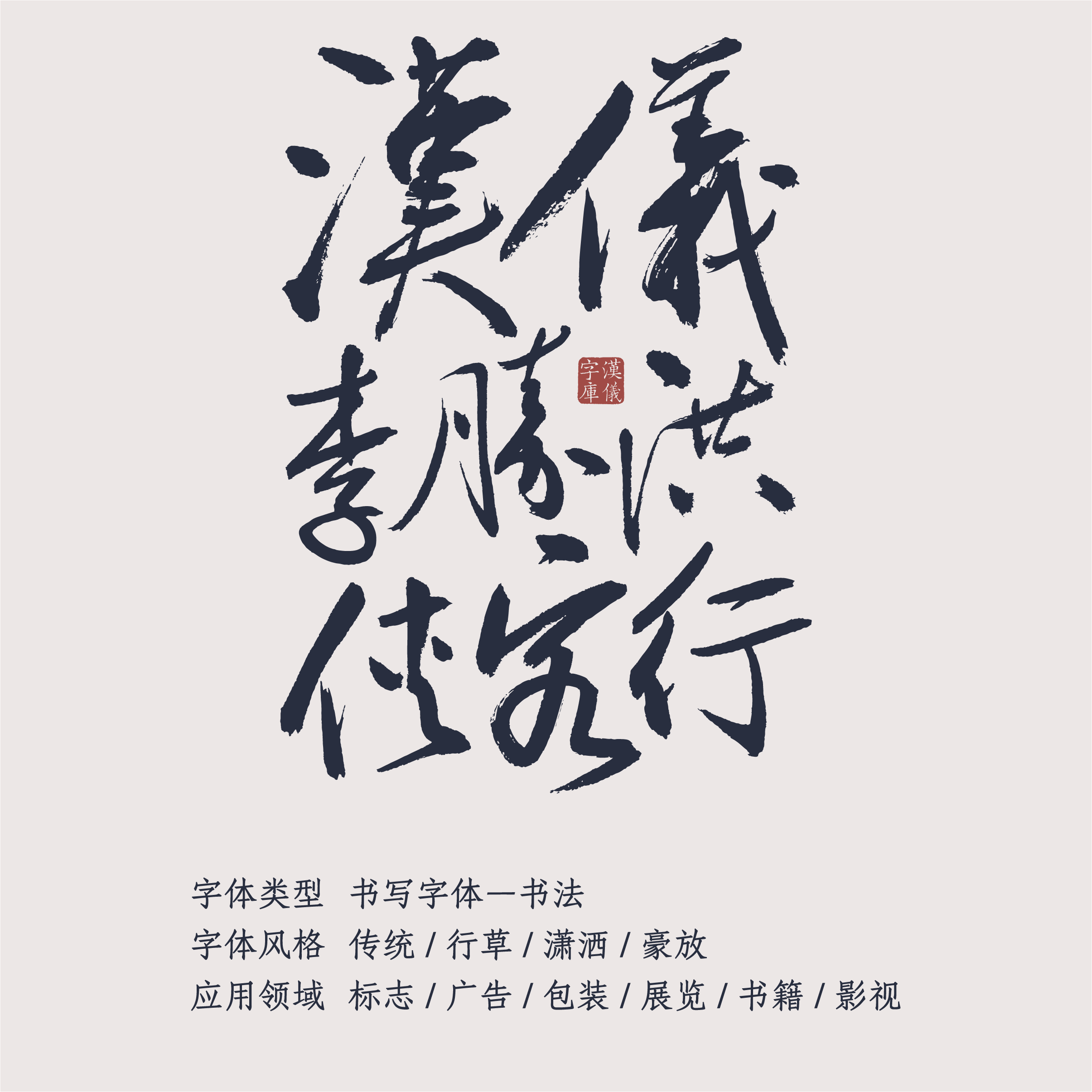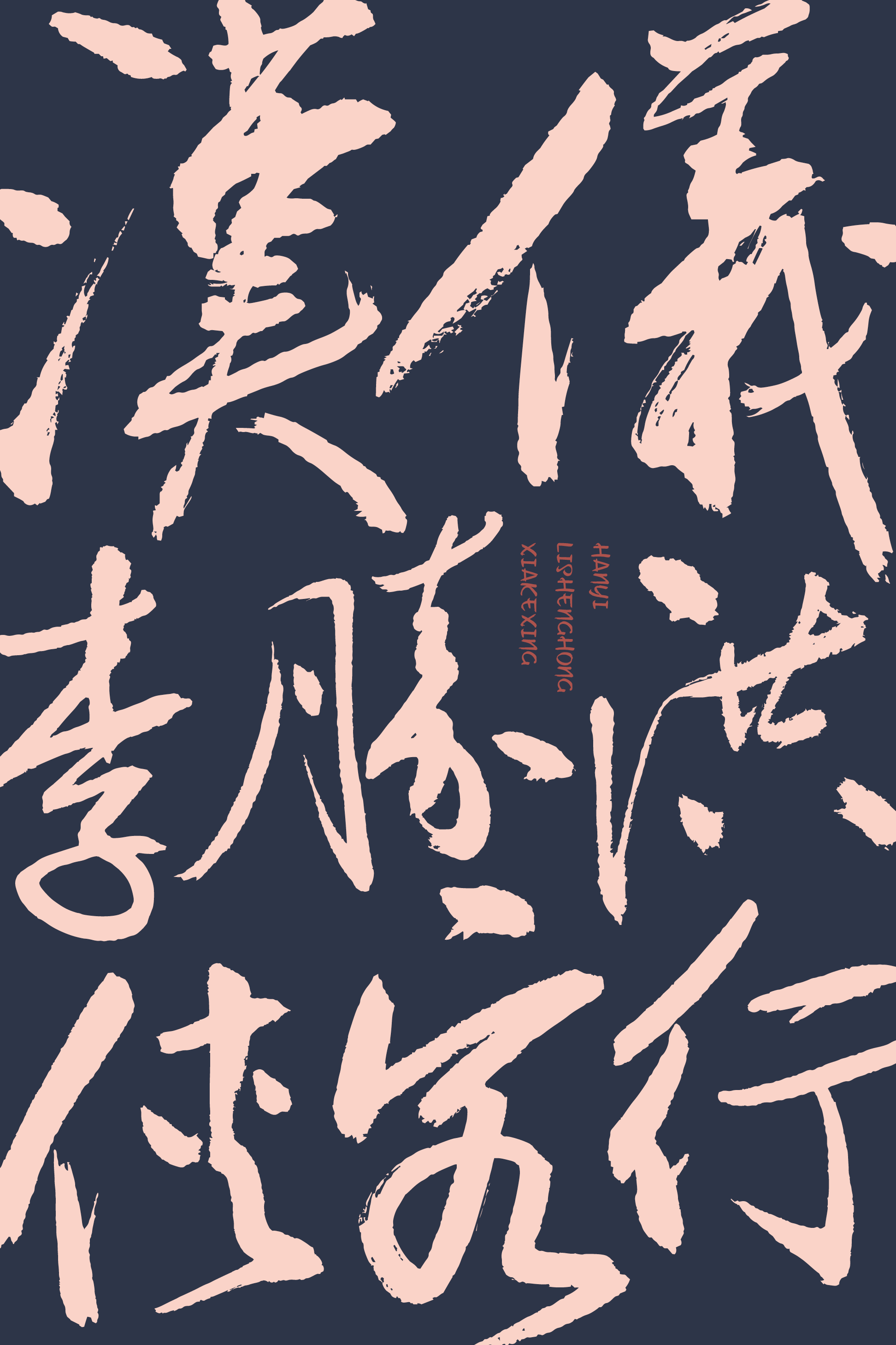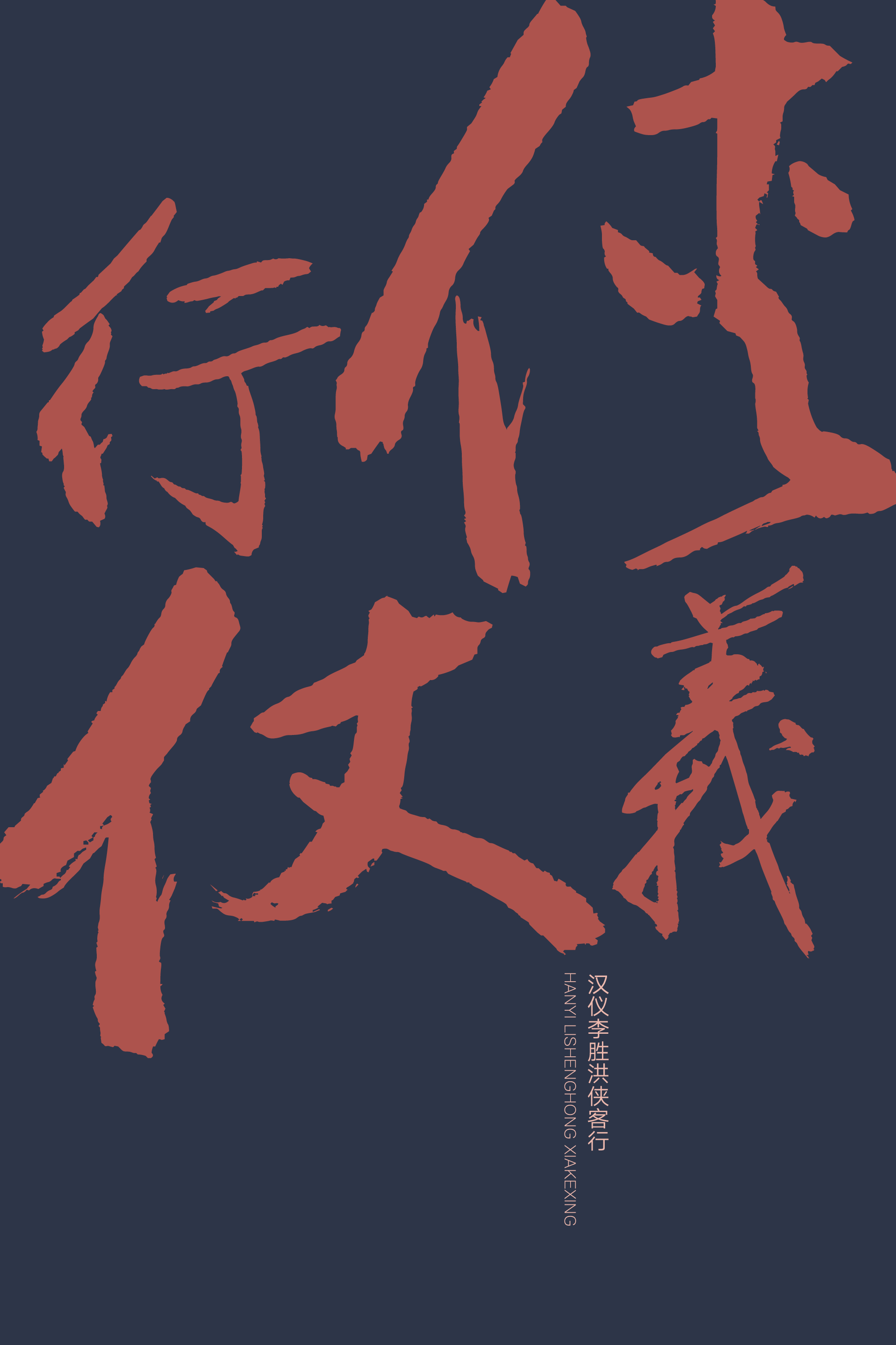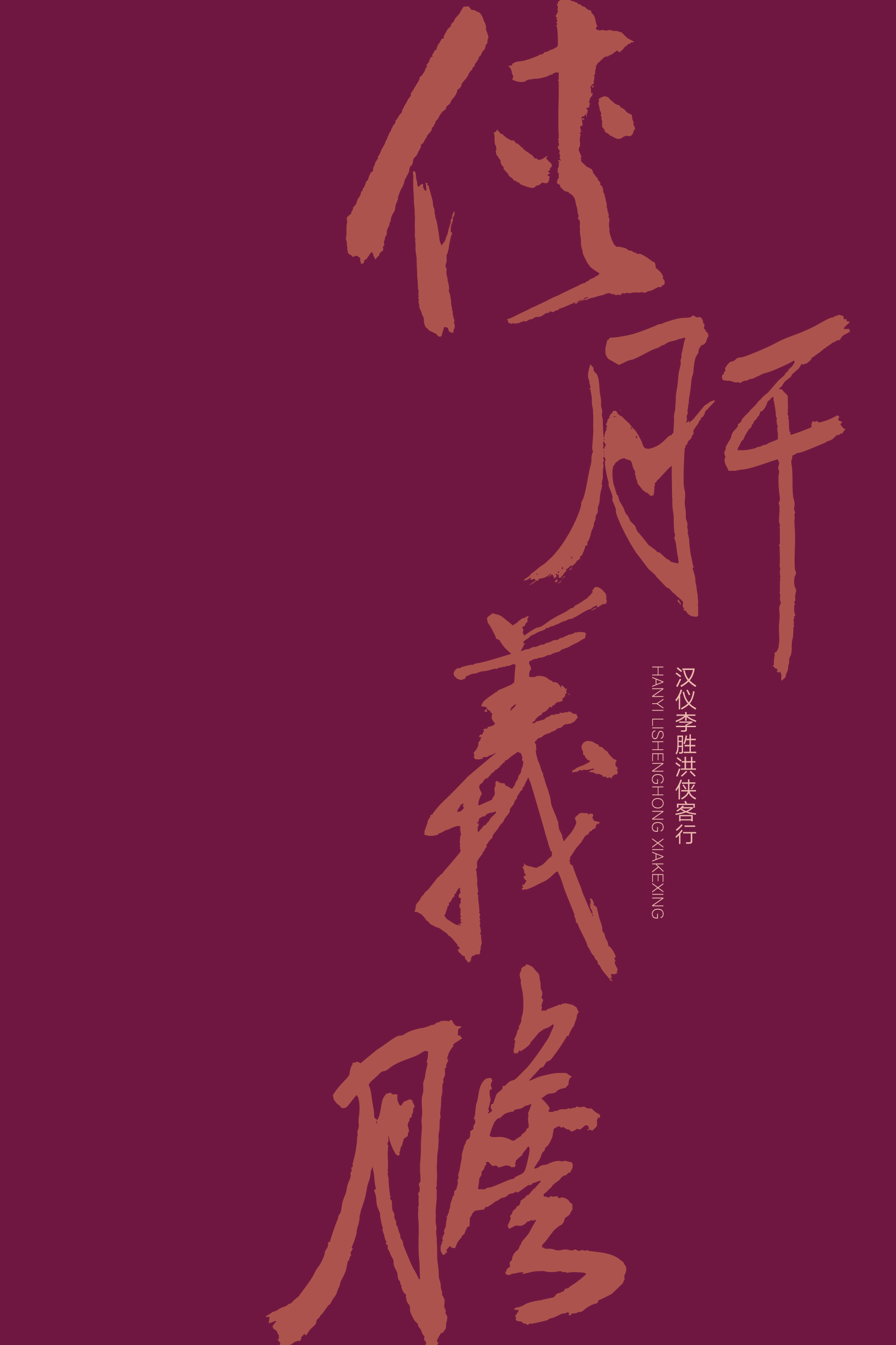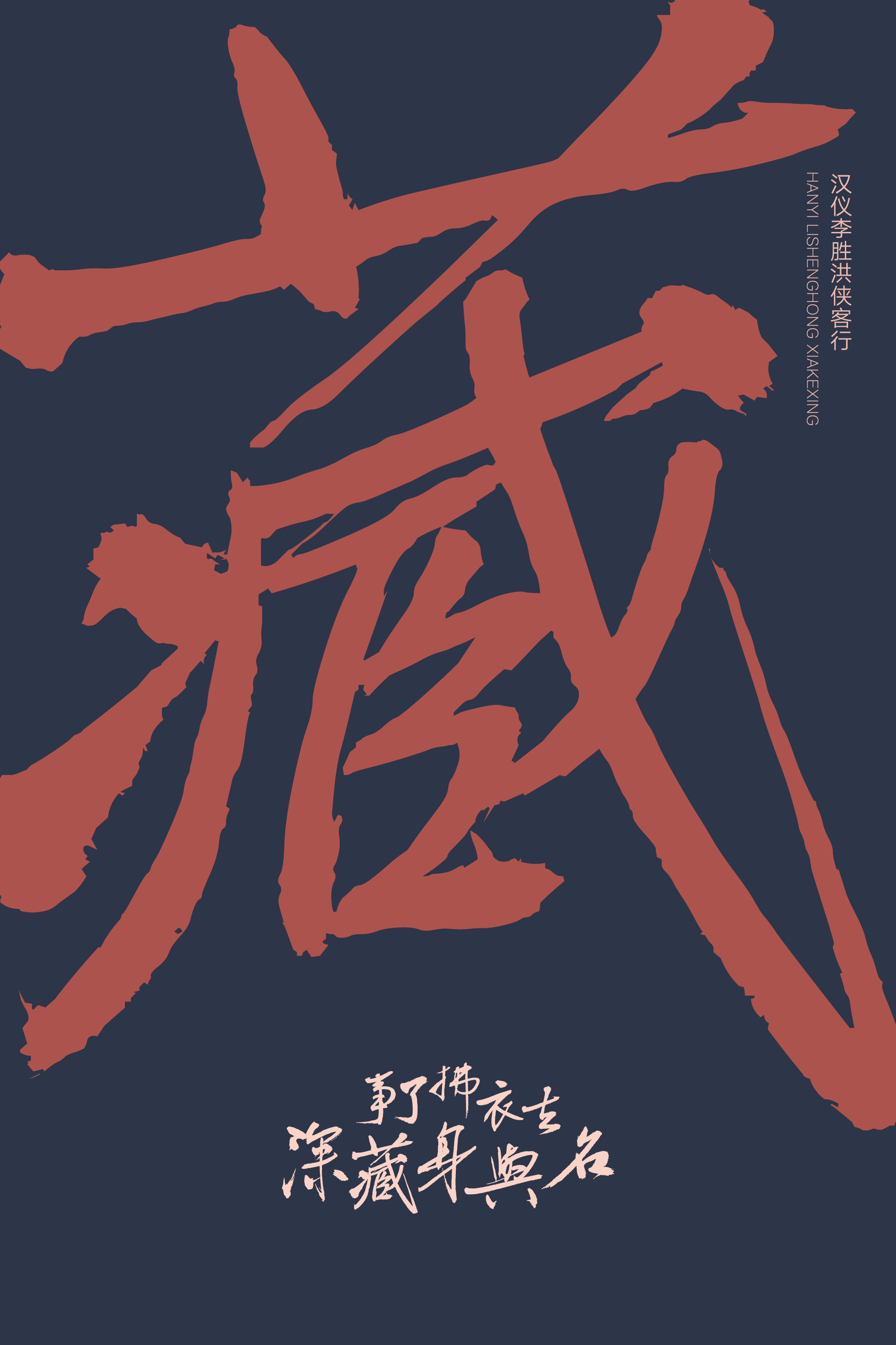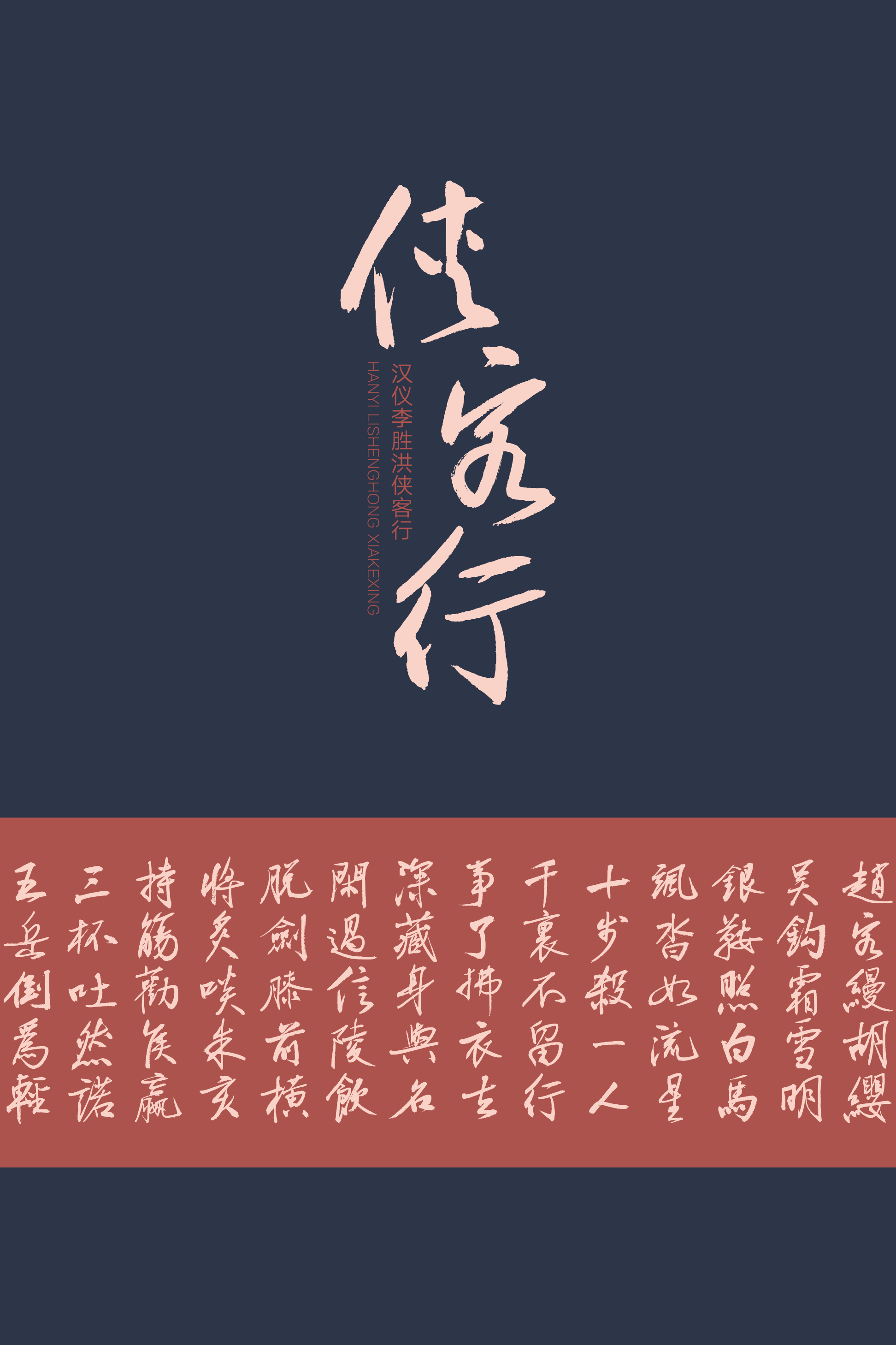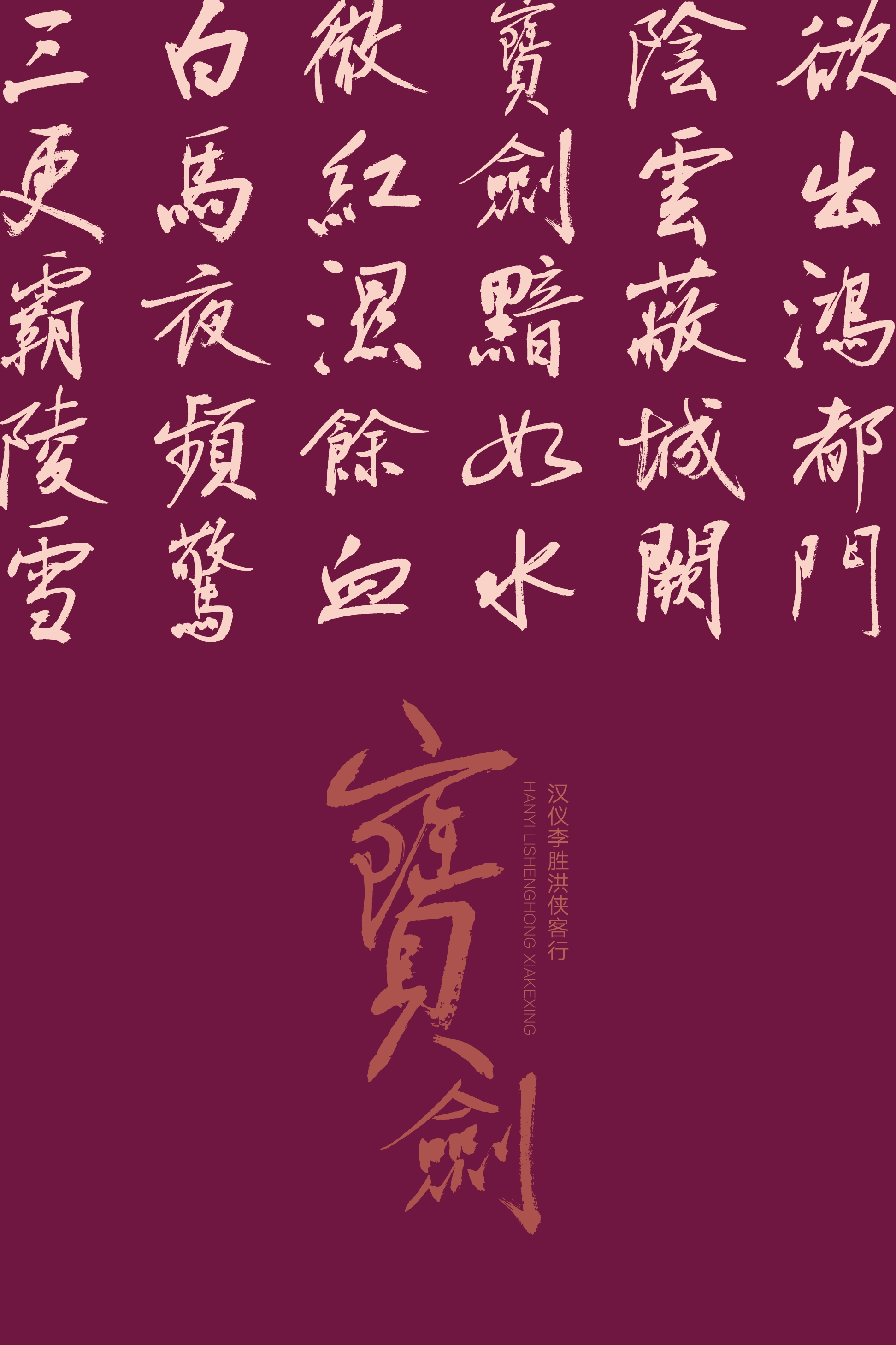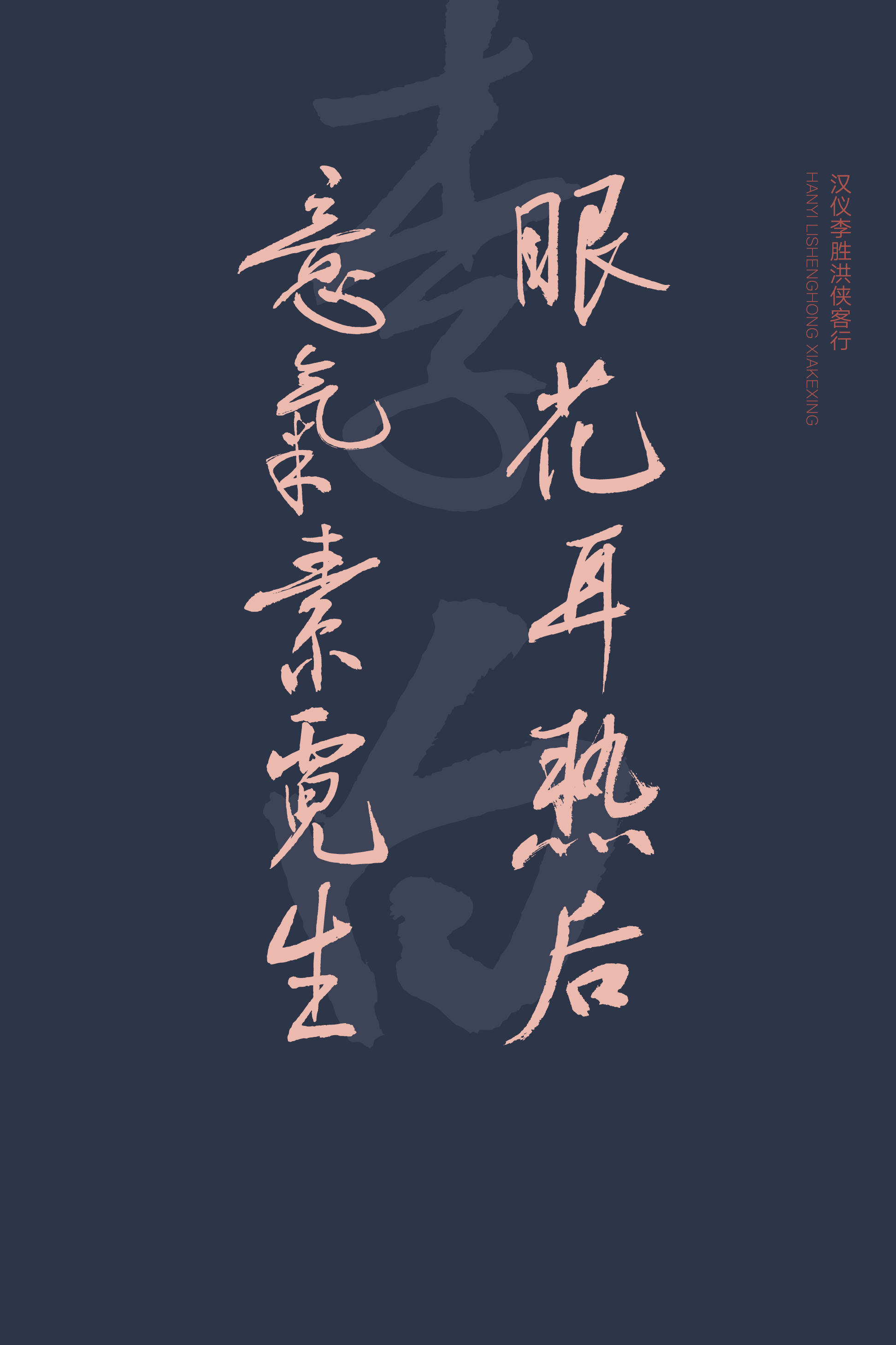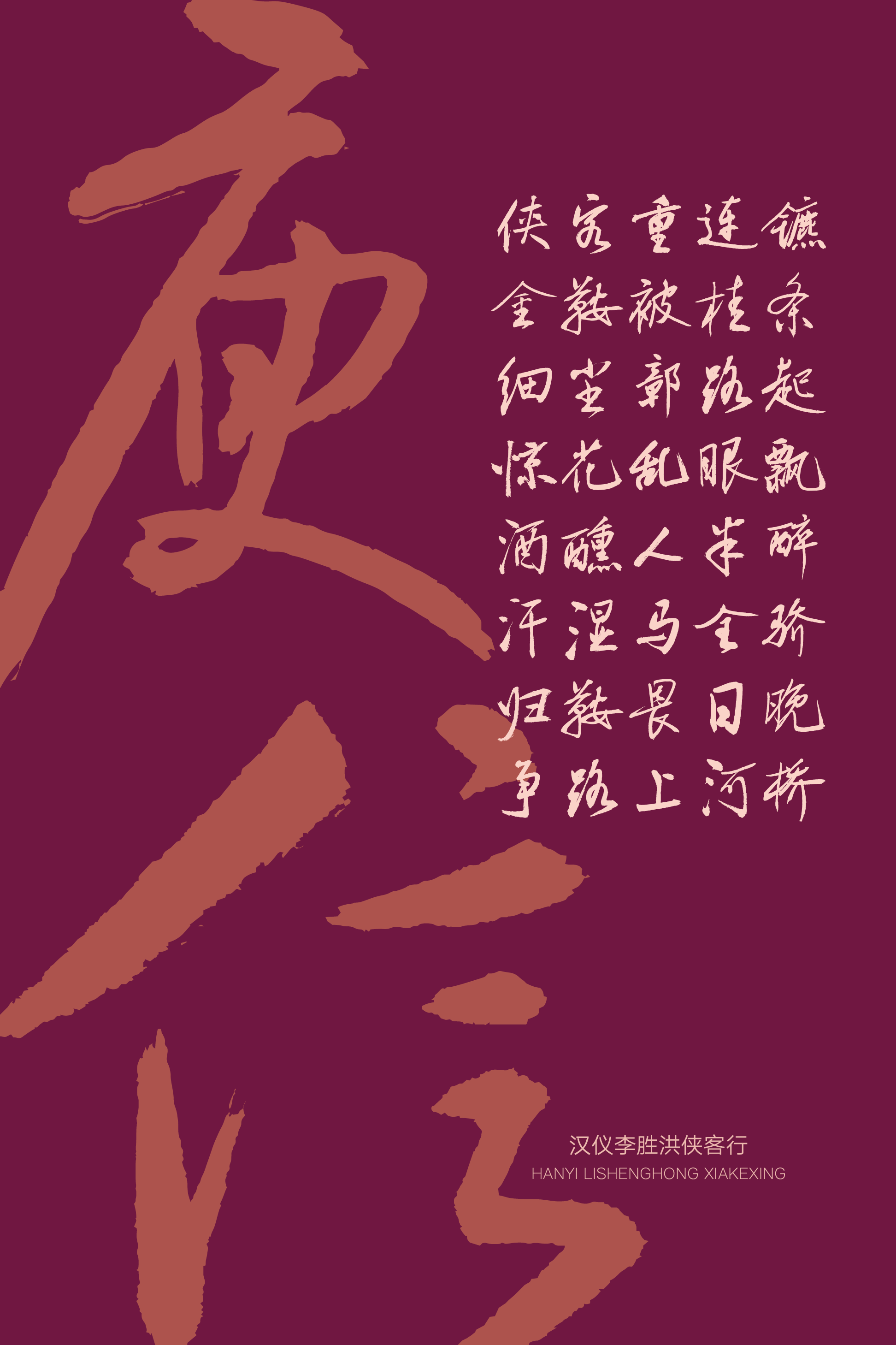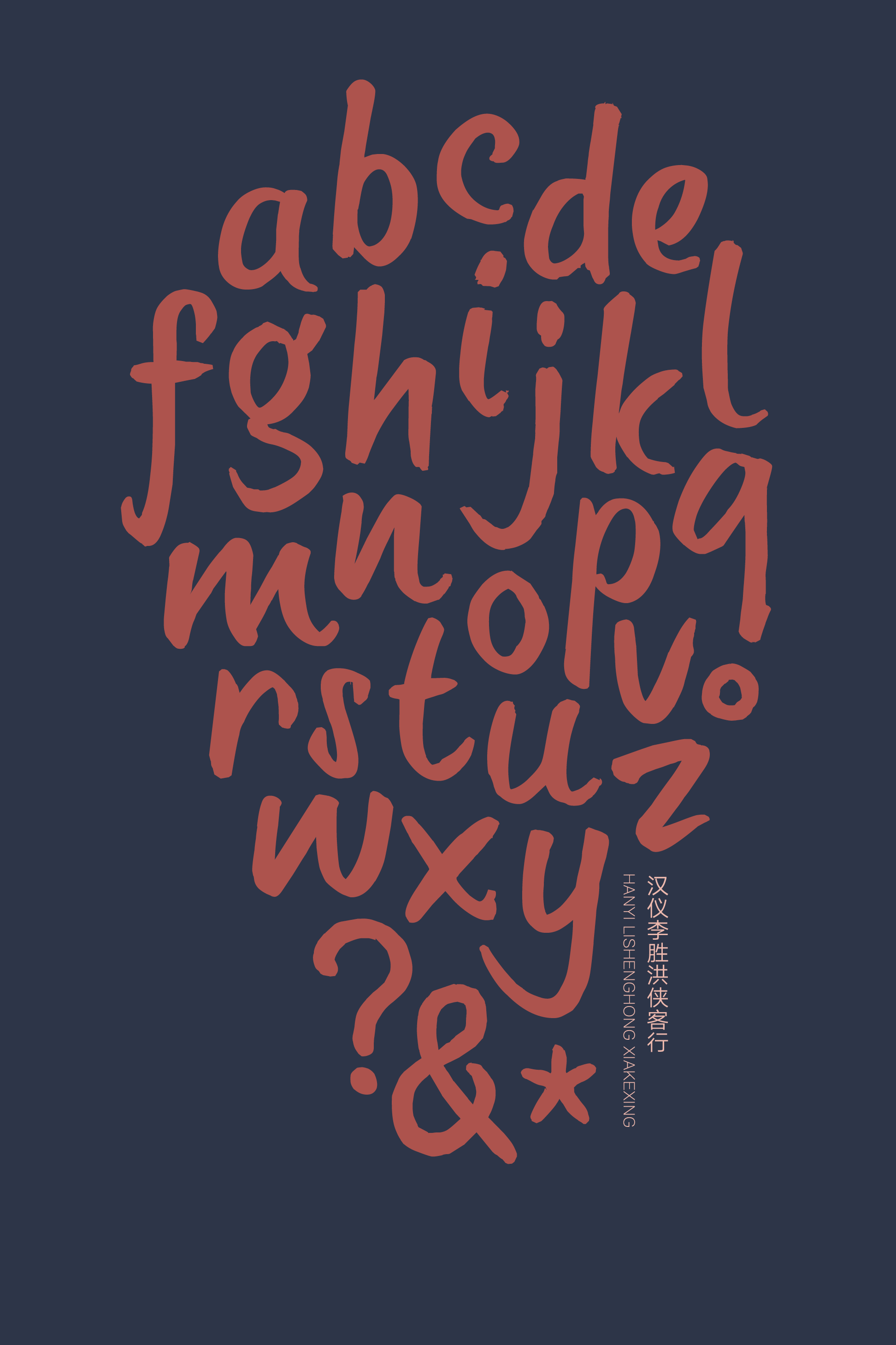
汉仪李胜洪侠客行
汉仪李胜洪侠客行,是一款由汉仪字库签约作者、书法家李胜洪先生书写的行草书法字体。整体恣意洒脱,中宫紧收,重心偏高,笔画细劲。下笔干脆利落,曲直相映,犀利如侠客招式,给人以侠气干云之感。这款书法字体古典意蕴深厚,可广泛应用于传统经典、历史文化、仙侠幻想等使用场景。气韵生于行草笔意流转之间,志趣清雅、超尘脱俗,好似李白笔下的侠客,事了拂衣去,深藏身与名。
李胜洪
字一谷,号樵翁
湖北荆州人
国家一级美术师,中国书法院创始人,享受国务院特殊津贴专家。
现为中国书法家协会理事、中国老年书画研究会副会长、中国美术馆专家委员会成员、全国书法(刻字)艺术作品展览评委。
曾任清华大学、中央美术学院等数所高校客座书法教授或担任书法高级研修班导师。近年来,因其对“我国书法事业的繁荣与发展作出的重要贡献”,两度被评为“中国书坛十大年度人物”。
中宫紧收,重心偏高,结构疏朗开张,有内紧外松之感。
笔画细劲,恣意洒脱。
笔锋犀利,曲直相映。
行草笔意流转,气韵清雅,超脱于尘世。